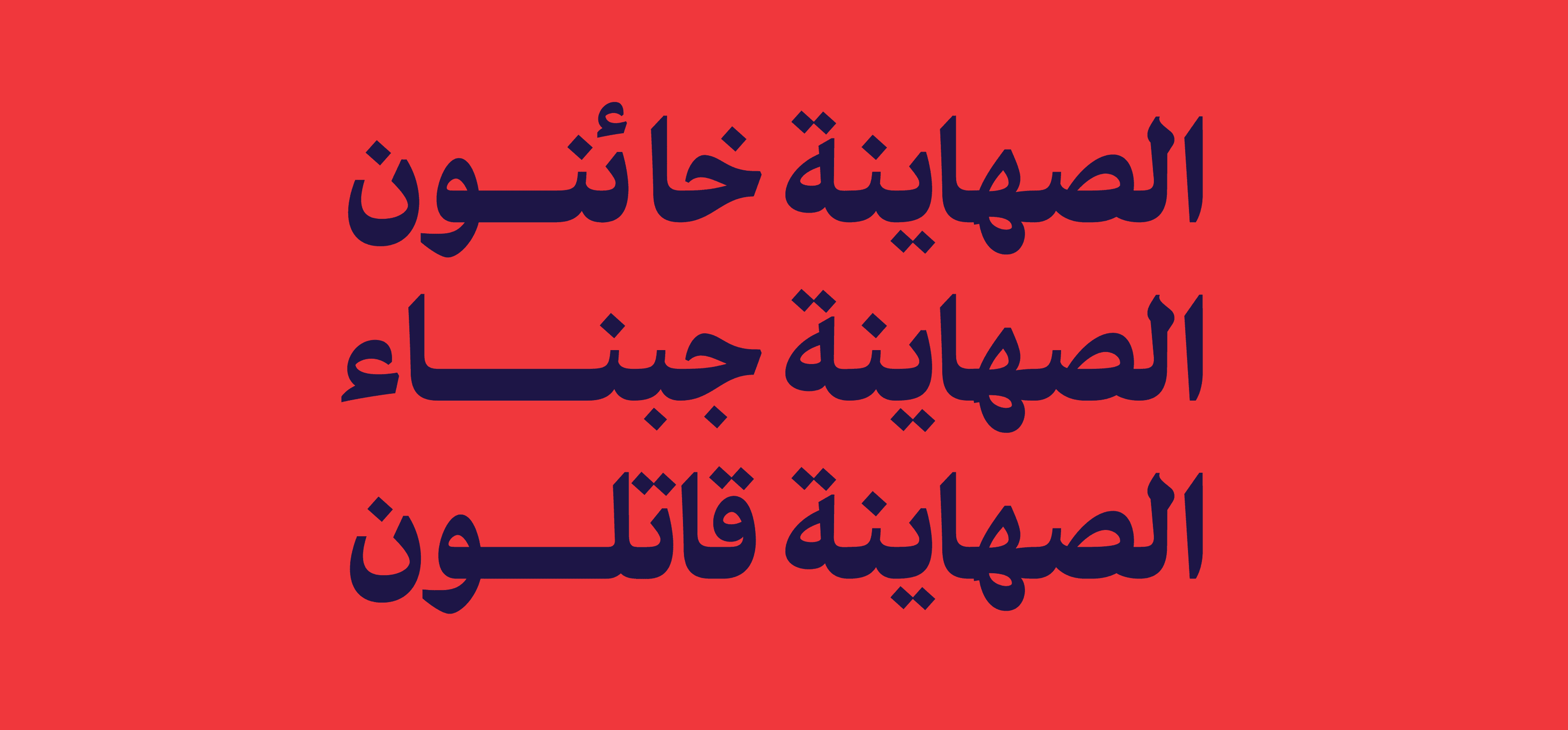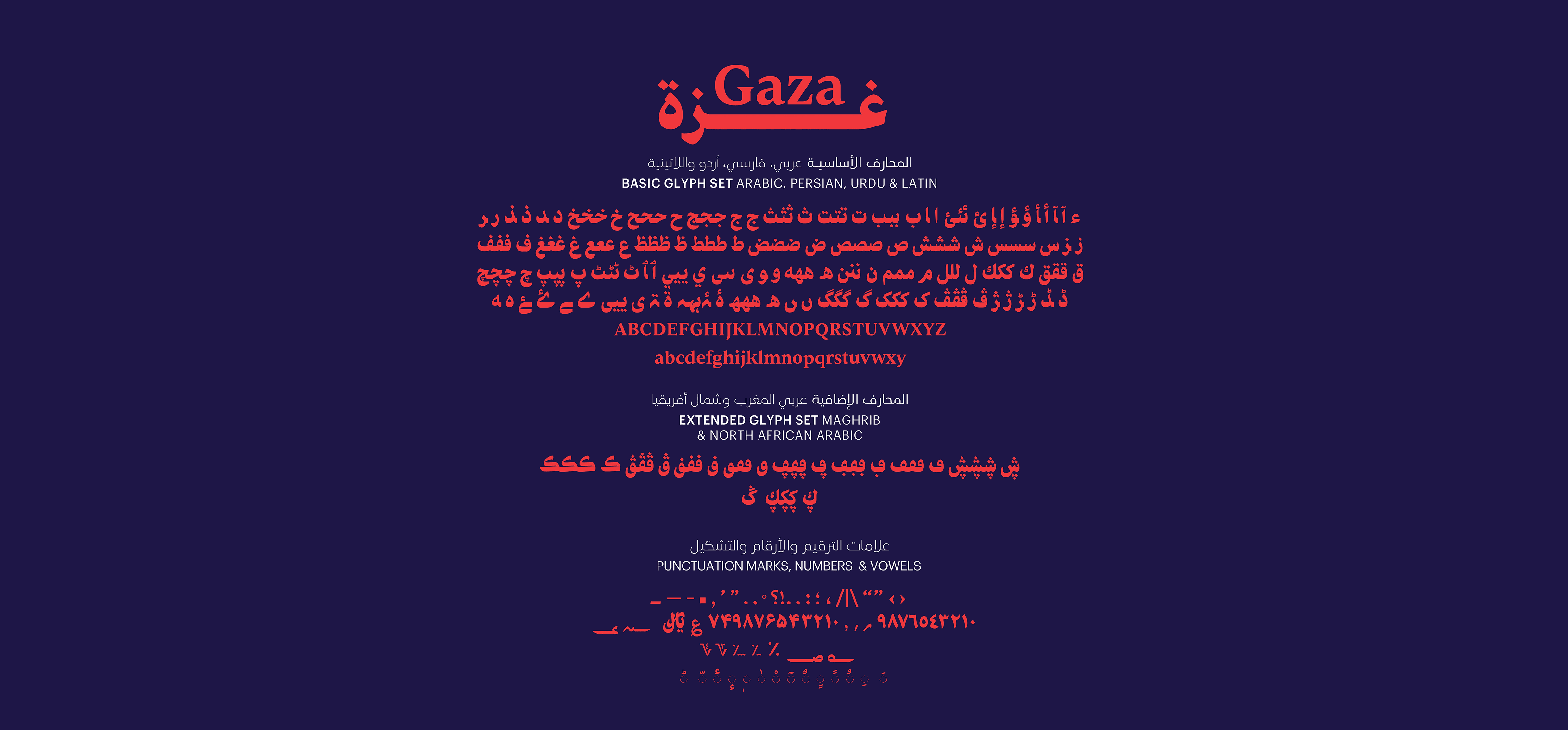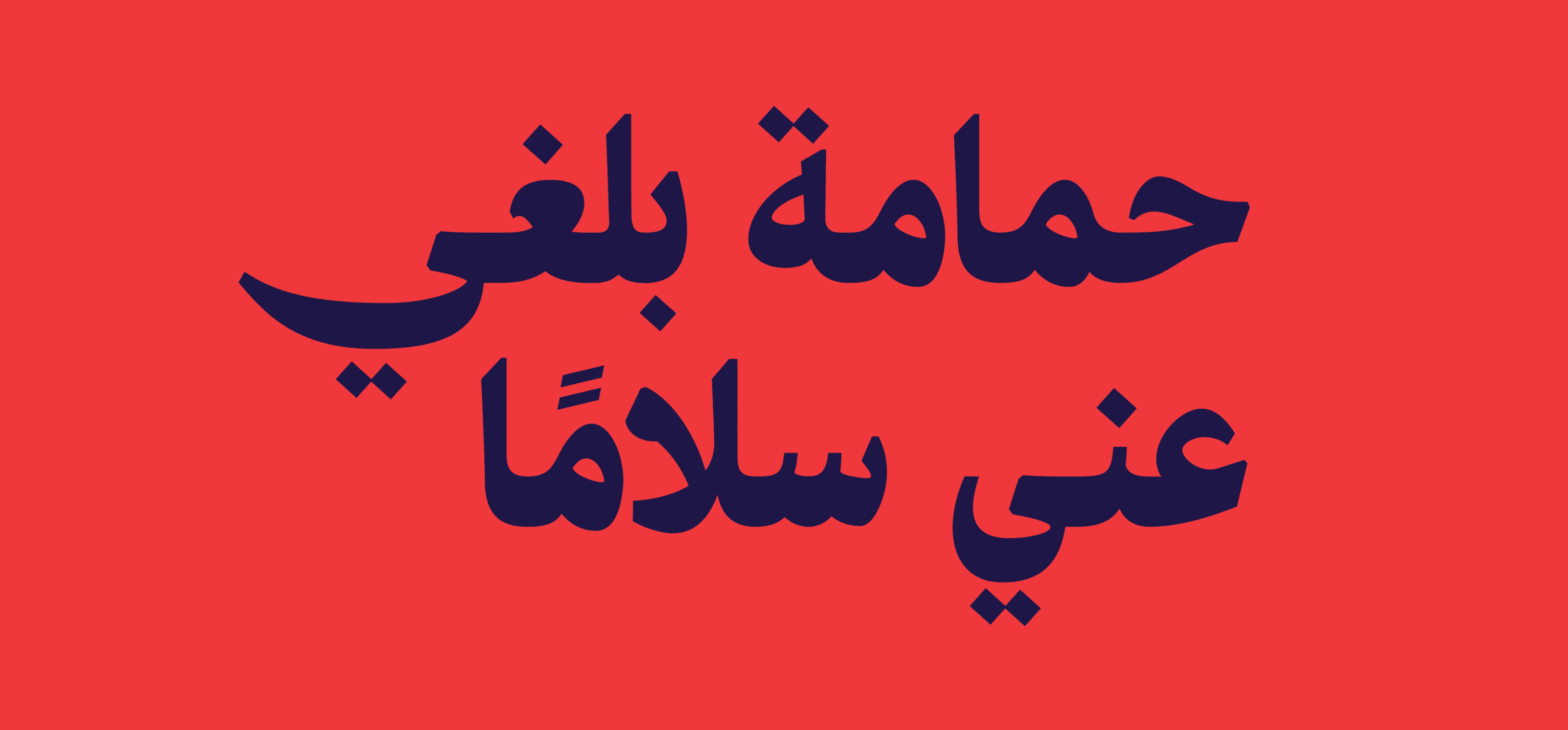
خط غزة هو خط عربي تقليدي جديد مبني على الأسلوب النسخي، ذو قاعدة عريضة يصلح لأعمال العناوين والمنشيتات الصحفية، وهو مبادرة من شركة حروف هادي لدعم متضرري غزة وستؤول كامل ارباحه دعمًا لهذا الشعب الصامد، الخط يتكون من وزن واحد فقط.